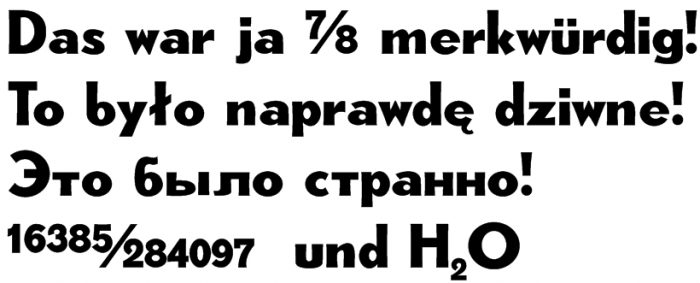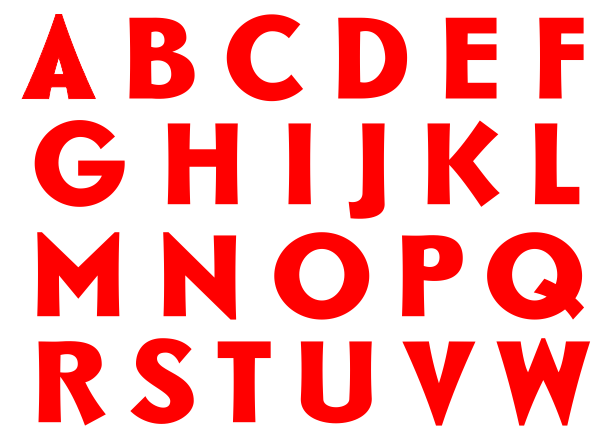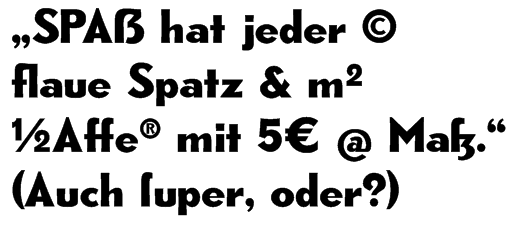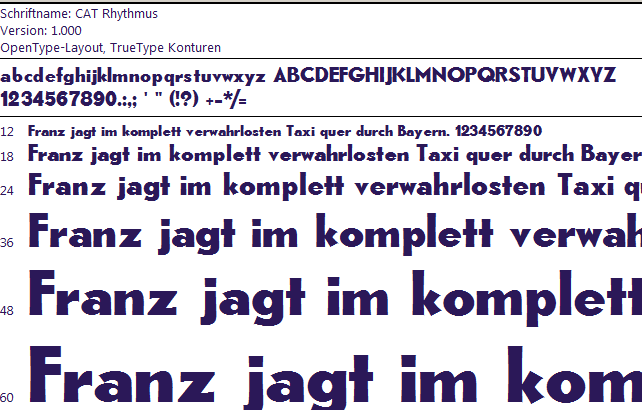
Typografie alter DDR-Akten
OK, ein 2. Tag Extrem-Fontlabbing und sie hat Kerning, OpenType-Ligaturen und noch ein wenig Feinschliff und ein ẞ. Und hier habe ich dann auch an die gedacht, die ẞ nichte auf der Tastatur haben: Einfach Sß eingeben, und es wird durch ẞ ersetzt. Weitete solche Hilfs-Ligaturen sind ©, ®, 1/2, 1/4, 3/4. Zudem alle Ligaturen aus der UNZ1-Liste mit ſ, f und 1-2 folgebuchstaben, und ch, ck, tt, ll, tz sind auch drin, und entweder über die OpenType-Ligatur oder wird diese nicht unterstützt üner die betreffenden Unicodes dargestellt. (Zum unterdrücken der Ligaturen ZWNJ verwenden)
:tuschel:  Hat sich in die LIGA-Tabelle ein Tippfehler eingeschlichen? Die Buchstabenfolge n-n erzeugt statt .
Aber sollten Geviert- und Halbgeviertstriche etwas fetter sein?
Stimmt, die können -- und sind jetzt auch fetter. Zudem hab ich noch mal ordentlich aufgebrätselt:
1. einige Glyphen die zu mager geraten waren im meinen Augen passend aufgefettet.
2. Ordentlich noch Akzent-Glyphen hinzugefügt, sodass wirklich jeder, der auf unserem Kontinent mit Lateinbuchstaben schreibt , die benutzen kann, auch meine Nachbarn hier, die Polen.
3. Ordentlich bei den Ziffern und OpenType zugelegt, so gibt es zusätzliche Tabellenziffern, und Zähler und Nenner für Brüche über frac, aber auch mehr Standardbrüche über die liga, für Software, die eben keine aktivierbaren OpenType-Funktionen unterstützt. 1/8, 1/4, 1/3, 3/8, 1/2, 5/8,  2/3 und 7/8 gibts über die Ligatur 1234567890/9876543210 geht über aktiviertes frac.
4. Wenn ich schon Richtung Osten schaue, ist in Brest nicht Schluss. Kyrillsche Lettern hab ich auch noch hinzugefügt
Sollten da noch ein paar Diakritika ein Stück nach links bzw. rechts rutschen dürfen?
ja. irgendwie hab ich noch nicht herausgefunden, wie man bei diesen die mitte festlegt, damit dieses automatische platzieren besser läuft.